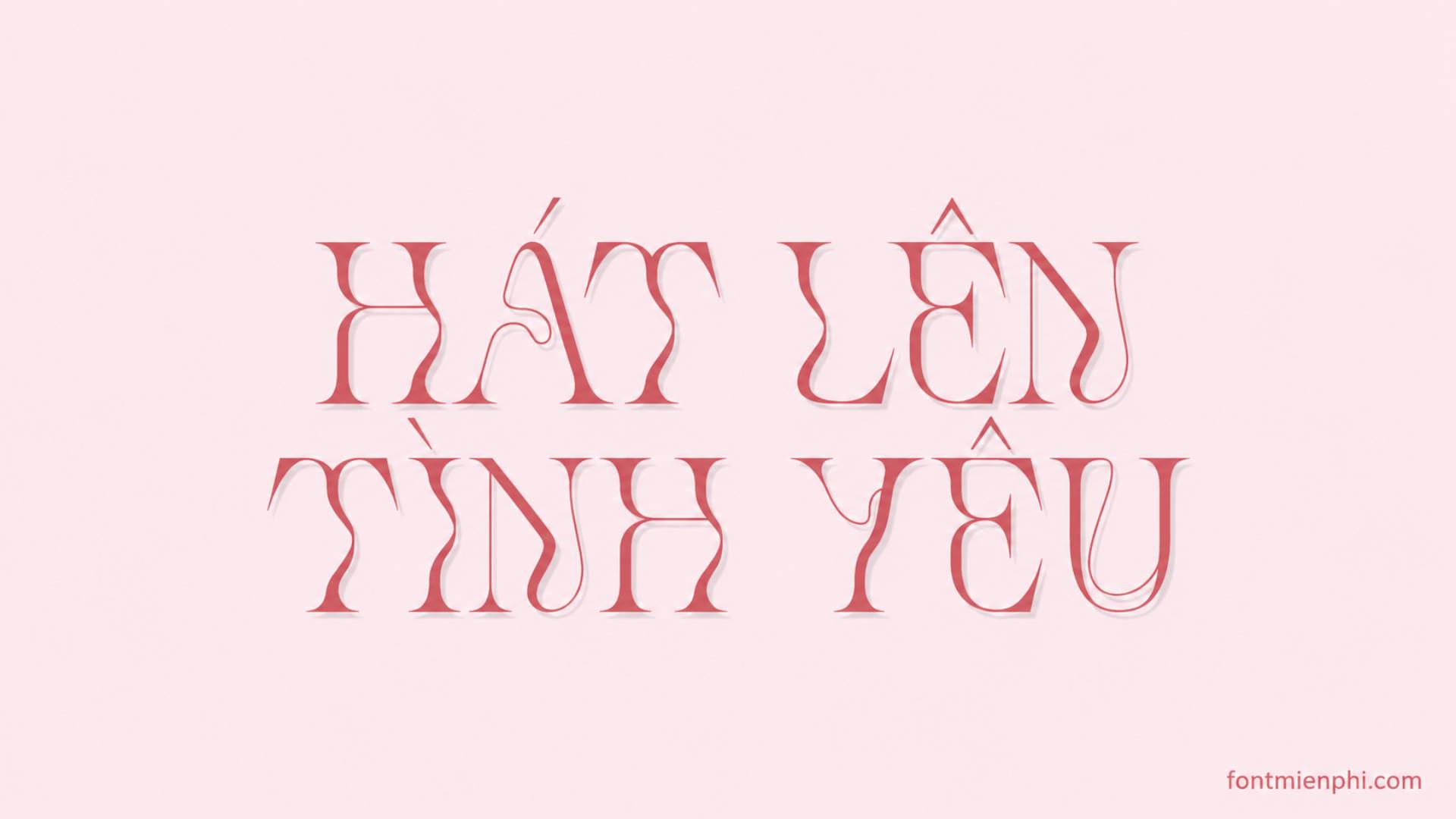
Tải Font Việt Hóa 1FTV VIP Welona – Cực Phẩm Dành Cho Thiết Kế Sang Trọng
Bạn đang tìm kiếm một phông chữ mang đậm nét thanh lịch, tinh tế để nâng tầm các dự án thiết kế cao cấp của mình? Font Việt hóa 1FTV VIP Welona chính là một trong những lựa chọn “đắt giá” nhất mà bạn không thể bỏ qua. Nằm trong bộ sưu tập VIP cao cấp, Welona mang đến một diện mạo hoàn toàn mới cho các ấn phẩm từ nhận diện thương hiệu đến thiệp cưới hay bao bì sản phẩm.
Hãy cùng khám phá chi tiết về nét mĩ miều của bộ font này và tải ngay phiên bản Việt hóa chuẩn xác nhất trong bài viết dưới đây.
1. Giới thiệu chung về Font 1FTV VIP Welona
1FTV VIP Welona là một kiệt tác typography được thiết kế với sự tỉ mỉ trong từng đường nét. Chữ “VIP” trong tên gọi đã phần nào khẳng định đẳng cấp của bộ font này. Nó không chỉ là một phông chữ thông thường mà là một công cụ đắc lực giúp các designer truyền tải trọn vẹn cảm xúc và sự sang trọng của thương hiệu.
Sở hữu những đường cong mềm mại, uyển chuyển nhưng vẫn giữ được sự rõ ràng và cấu trúc vững chắc, Welona tạo ra một nhịp điệu thị giác vô cùng lôi cuốn. Phiên bản Việt hóa bởi đội ngũ 1FTV đã được xử lý kỹ lưỡng từng dấu câu, đảm bảo khi gõ tiếng Việt, các ký tự vẫn giữ nguyên được cái hồn và sự cân đối của thiết kế gốc.
2. Đặc điểm nổi bật của Font Welona Việt hóa
Tại sao 1FTV VIP Welona lại được giới thiết kế săn đón đến vậy? Dưới đây là những lý do chính:
• Thiết kế sang trọng và độc bản: Các nét thanh đậm (contrast) được xử lý mượt mà, tạo cảm giác cao cấp, rất phù hợp với xu hướng thiết kế hiện đại.
• Kerning (Khoảng cách chữ) hoàn hảo: Đội ngũ Việt hóa đã tinh chỉnh lại khoảng cách giữa các ký tự có dấu trong tiếng Việt để chữ không bị dính hay rời rạc, mang lại trải nghiệm đọc mượt mà nhất.
• Hỗ trợ đầy đủ ký tự tiếng Việt (Vietnamese Glyphs): Tạm biệt nỗi lo lỗi font chữ, lệch dấu hay bị “ô vuông”. Bạn có thể tự tin gõ bất kỳ đoạn văn bản tiếng Việt nào.
• Bộ ký tự thay thế đa dạng (Alternates & Ligatures): Font cung cấp nhiều nét gạch nối và ký tự thay thế nghệ thuật, giúp thiết kế của bạn trông tự nhiên và có tính “handcrafted” (làm thủ công) cao hơn.
3. Ứng dụng thực tế của 1FTV VIP Welona
Với vẻ đẹp kiêu sa và thanh lịch, Font 1FTV VIP Welona là “vũ khí bí mật” cho nhiều loại hình dự án khác nhau:
Gợi ý thiết kế: Để phát huy tối đa vẻ đẹp của Welona, hãy sử dụng nó cho các tiêu đề (Heading) kích thước lớn, kết hợp cùng một font Sans-serif tối giản (như Montserrat hoặc Cuprum) cho phần nội dung (Body text) để tạo sự tương phản đầy ấn tượng.
• Thiết kế nhận diện thương hiệu (Branding): Tuyệt vời để làm Logo, Slogan cho các thương hiệu thời trang, mỹ phẩm, spa, thẩm mỹ viện hay trang sức cao cấp.
• Thiết kế thiệp cưới (Wedding Invitations): Mang lại sự lãng mạn, bay bổng và vô cùng tinh tế cho những tấm thiệp mời ngày trọng đại.
• Bao bì sản phẩm (Packaging): Nâng tầm giá trị sản phẩm, đặc biệt là các mặt hàng organic, nước hoa, hoặc thực phẩm cao cấp.
• Typography & Trích dẫn (Quotes): Rất phù hợp để chèn chữ nghệ thuật lên hình ảnh trên các trang mạng xã hội (Facebook, Instagram).